Majdnem napra pontosan 2 éve indultam el a kalligráfia útján. Sokan kérdezték, hogy miért a kalligráfia, bevallom, nem tudom a választ. Mindig elbűvöltek ezek a csodálatos betűk, illetve az írószerek. Gyerekként, az iskolában is töltőtollat használtam, aztán jött az egyetem, ott bevallom, már nem írtam annyit 😉, és végül a munkahelyen abszolút digitális vagyok, még jegyzetelni is a laptopomon szoktam. Szóval már nem kellett járnom az írószerboltba, legnagyobb sajnálatomra, pedig az iskolakezdésben ezt szerettem a legjobban. Az új írószereket, az írószerbolt illatát. Nade elkanyarodtam.
Először 4 éve vettem részt egy kalligráfia workshopon, ahol, mint utólag kiderült, nem a célravezető módszerrel próbáltak bevezetni ebbe a művészetbe, de nem adtam fel, és mindig kerestem a lehetőséget.
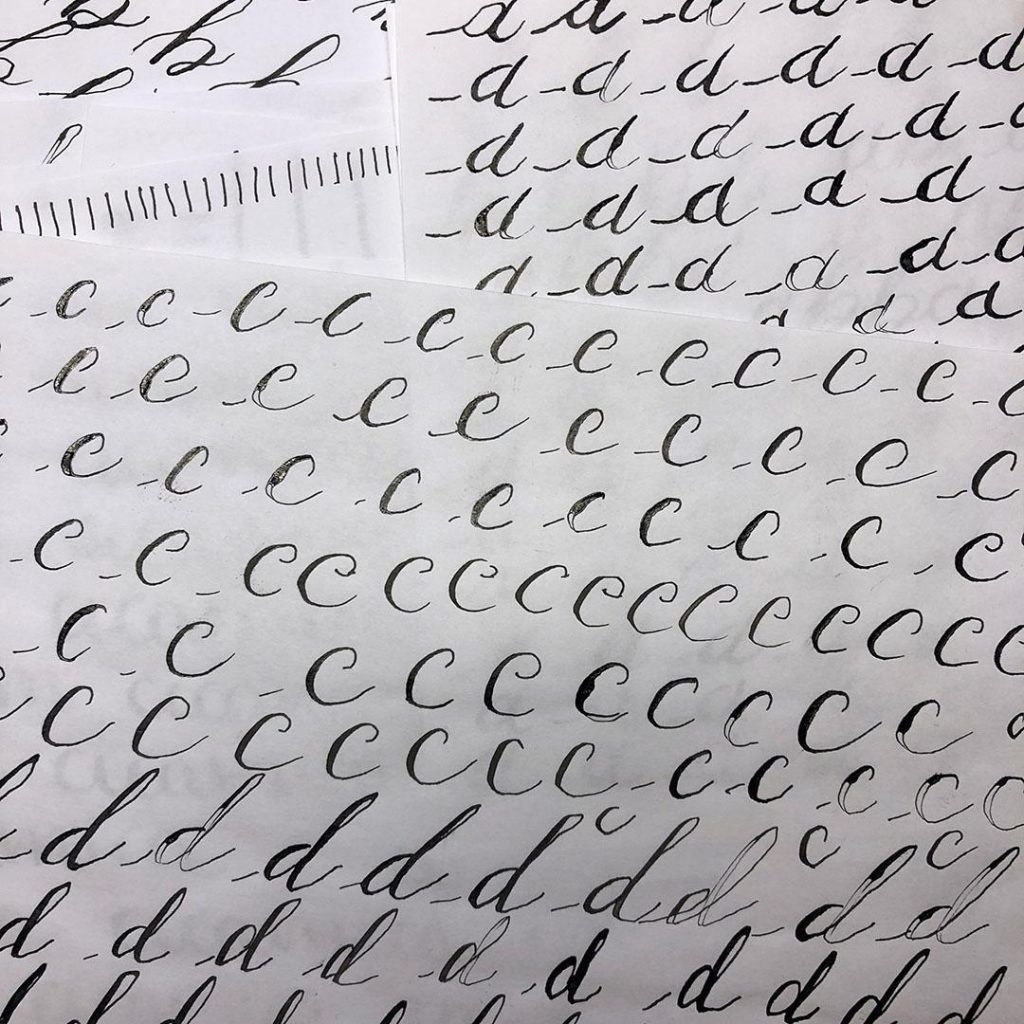
Ez a lehetőség 2 évvel később a pandémia közepén jött el, amikor rátaláltam Annára a Facebookon, és innen számítom az igazi kezdést. Ha jól emlékszem hétfőn, szerdán és pénteken élőben mutatta meg a faux kalligráfiát, és mutatta meg a módszert, ami az igazi áttörést jelentette, az alapvonásokat. Onnan pedig nem volt megállás, nagyon élveztem, és azóta is élvezem. Teljesen kikapcsol, és mindig találok valamit, amivel tudom fejleszteni magam. A kalligráfia nagyon gyakran együtt jár az akvarell festéssel, ez az esetemben sem volt másképp, szóval néhány hónappal később már elkezdtem az ecsetet is forgatni a toll mellett. Azóta is ingadozom a két hobbi között, hol az egyik, hol a másik erősebb. Amikor-e sorokat írom épp a kalligráfia van túlsúlyban.
Persze visszatértem az írószerboltokba is, elképesztő, hogy micsoda bőség van, és mennyi csoda! Nagyon veszélyesek ezek a helyek, mert 1-1 darab viszonylag olcsó, és akkor elkezdesz pakolni… Viszonylag rövid idő alatt elég tetemes készletet sikerült felhalmozni, nade erről is majd később. 😊
Nagyon sokat tanultam és tapasztaltam, ezért arra gondoltam, hogy elindítok egy blogot, ahol megosztom Veletek, hogy hogyan tudtok Ti is sikeresen elindulni a kalligráfia és az akvarell festés útján.